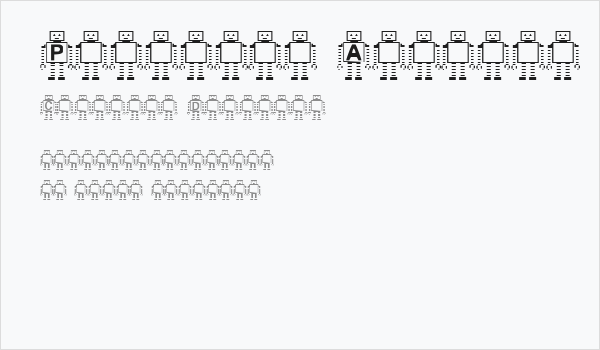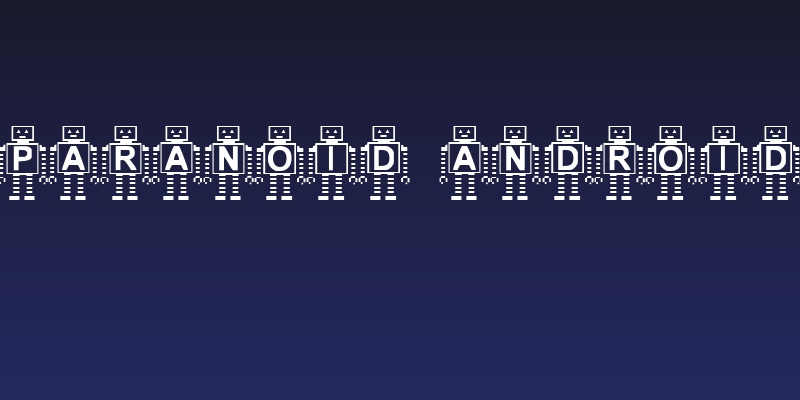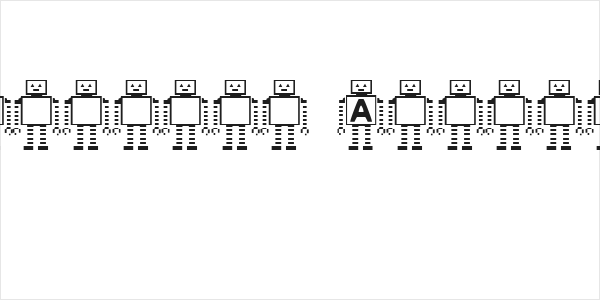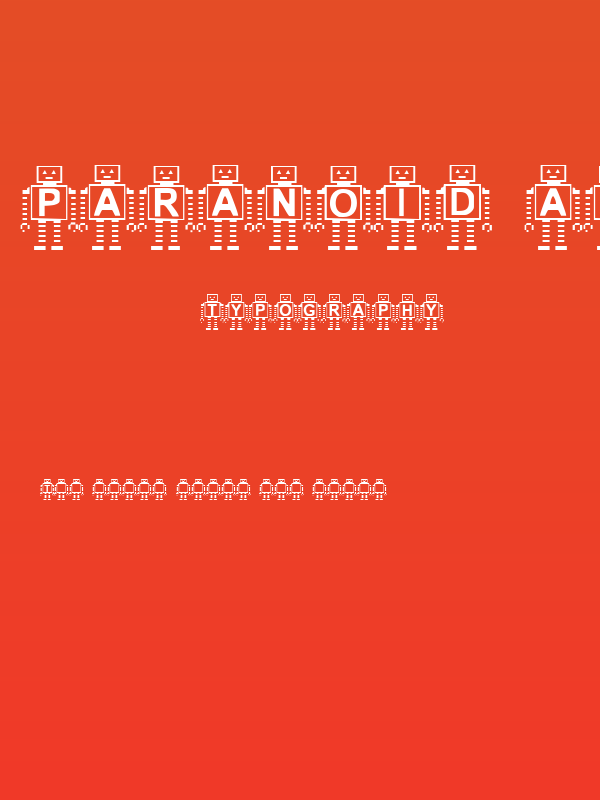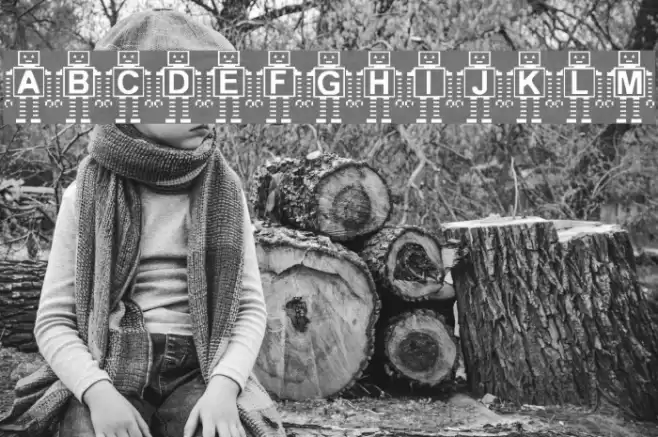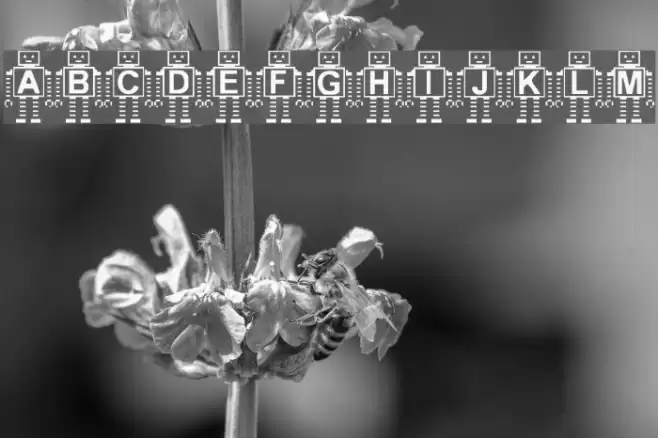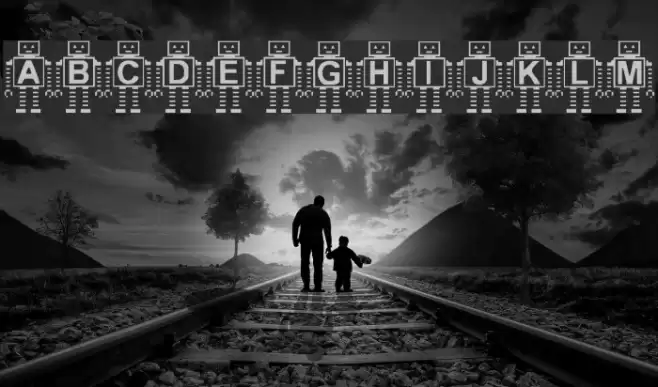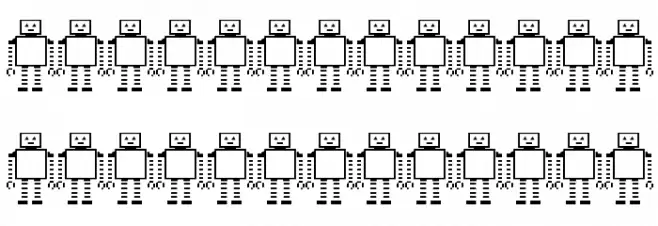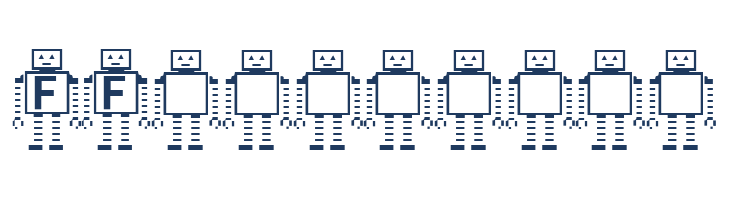
Paranoid Android Font
| Style général | Futuristic, Playful |
| Cas d'utilisation | Logos, Posters, Headlines |
| Projets proposés | Ideal for children's books, tech-themed posters, video game graphics, and educational materials. |